الطباعة على الويب
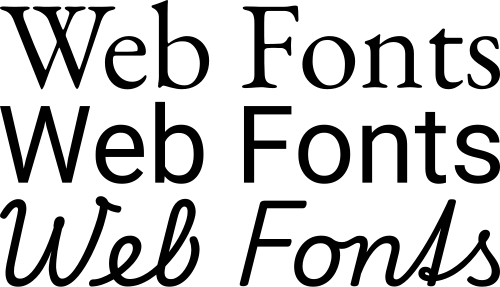
تُعنى الطباعة على الويب ، كغيرها من فنون الطباعة ، بتصميم الصفحات ، بما في ذلك تخطيطها واختيار أنواع الخطوط . وعلى عكس الطباعة التقليدية المعتمدة على الطباعة (حيث تكون الصفحة ثابتة بعد طباعتها )، فإن الصفحات المُخصصة للعرض على شبكة الإنترنت العالمية تواجه تحديات تقنية إضافية، وتتيح في الوقت نفسه فرصًا أوسع نظرًا لقدرتها على تغيير العرض ديناميكيًا . كانت تصاميم صفحات الويب الأولى بسيطة للغاية بسبب محدودية التكنولوجيا؛ أما التصاميم الحديثة فتستخدم أوراق الأنماط المتتالية (CSS) وجافا سكريبت وتقنيات أخرى لتحقيق رؤية مصمم الخطوط والعميل.
عند إنشاء لغة HTML لأول مرة، كانت أنواع الخطوط وأنماطها تُتحكم بها حصريًا إعدادات كل متصفح ويب . لم تكن هناك آلية تُمكّن صفحات الويب الفردية من التحكم في عرض الخط حتى قدمت نتسكيبfont عنصر <script> في عام 1995، والذي تم توحيده لاحقًا في مواصفات HTML 3.2. مع ذلك، كان يجب تثبيت خط الكمبيوتر المُحدد بواسطة عنصر <script> على جهاز المستخدم، أو استخدام خط احتياطي، مثل خط sans-serif أو monospacefont الافتراضي للمتصفح . نُشرت أول مواصفات CSS في عام 1996، ووفرت نفس الإمكانيات.
صدرت مواصفات CSS2 عام 1998، وسعت إلى تحسين عملية اختيار الخطوط بإضافة ميزات مطابقة الخطوط وتوليفها وتنزيلها. لم تلقَ هذه التقنيات رواجًا كبيرًا، وتم حذفها في مواصفات CSS2.1. مع ذلك، أضاف متصفح إنترنت إكسبلورر دعمًا لميزة تنزيل الخطوط في الإصدار 4.0 ، الذي صدر عام 1997. [ 1 ] أُدرجت ميزة تنزيل الخطوط لاحقًا في وحدة خطوط CSS3، ومنذ ذلك الحين تم تطبيقها في متصفحات سفاري 3.1 وأوبرا 10 وموزيلا فايرفوكس 3.5 . وقد أدى ذلك إلى زيادة الاهتمام بتصميم الخطوط على الويب، فضلًا عن زيادة استخدام ميزة تنزيل الخطوط.
CSS1
في أول مواصفات CSS، [ 2 ] حدد المؤلفون خصائص الخط من خلال سلسلة من الخصائص:
font-familyfont-stylefont-variantfont-weightfont-size
تم تحديد جميع الخطوط بالاسم فقط. وبخلاف الخصائص المذكورة أعلاه، لم يكن لدى المصممين أي وسيلة لتنسيق الخطوط، ولم تكن هناك آلية لاختيار الخطوط غير الموجودة على نظام العميل.
خطوط آمنة للاستخدام على الويب
الخطوط الآمنة للويب هي خطوط حاسوبية يُتوقع وجودها على نطاق واسع من أنظمة الحاسوب ، ويستخدمها مُنشئو محتوى الويب لزيادة احتمالية عرض المحتوى بالخط المُختار. إذا لم يكن لدى زائر موقع ويب الخط المُحدد، يحاول متصفحه اختيار بديل مشابه، بناءً على الخطوط الاحتياطية التي حددها المُنشئ والعائلات العامة ، أو يستخدم استبدال الخطوط المُعرّف في نظام تشغيل الزائر.
خطوط مايكروسوفت الأساسية للويب
لضمان حصول جميع مستخدمي الإنترنت على مجموعة أساسية من الخطوط، أطلقت مايكروسوفت مبادرة الخطوط الأساسية للويب عام ١٩٩٦ (والتي انتهت عام ٢٠٠٢). وتشمل الخطوط المتاحة Arial و Courier New و Times New Roman و Comic Sans و Impact و Georgia و Trebuchet و Webdings و Verdana ، وذلك بموجب اتفاقية ترخيص المستخدم النهائي التي سمحت بتوزيعها بحرية مع تقييد بعض حقوق استخدامها. وقد جعلها انتشارها الواسع عنصرًا أساسيًا لمصممي مواقع الويب. ومع ذلك، لا تتضمن معظم توزيعات لينكس هذه الخطوط افتراضيًا.
سعت CSS2 إلى زيادة الأدوات المتاحة لمطوري الويب من خلال إضافة توليف الخطوط، وتحسين مطابقة الخطوط، وإمكانية تنزيل الخطوط عن بُعد. [ 3 ]
تمت إزالة بعض خصائص الخطوط في CSS2 من CSS2.1 ثم أُضيفت لاحقًا إلى CSS3. [ 4 ] [ 5 ]
الخطوط الاحتياطية
تسمح مواصفات CSS بإدراج عدة خطوط كخطوط احتياطية. [ 6 ] في CSS، font-familyتقبل الخاصية قائمة بأنواع الخطوط مفصولة بفواصل، كما يلي:
font-family : "Nimbus Sans L" , Helvetica , Arial , sans-serif ;الخط الأول المحدد هو الخط المفضل. إذا لم يكن هذا الخط متوفرًا، يحاول متصفح الويب استخدام الخط التالي في القائمة. إذا لم يتم العثور على أي من الخطوط المحددة، يعرض المتصفح خطه الافتراضي. وتتكرر هذه العملية نفسها لكل حرف على حدة إذا حاول المتصفح عرض حرف غير موجود في الخط المحدد.
عائلات الخطوط العامة
لمنح مصممي المواقع الإلكترونية بعض التحكم في مظهر الخطوط على صفحاتهم، حتى في حال عدم توفر الخطوط المحددة، تسمح مواصفات CSS باستخدام عدة عائلات خطوط عامة. صُممت هذه العائلات لتقسيم الخطوط إلى فئات متعددة بناءً على مظهرها العام. وعادةً ما تُحدد كخيار أخير ضمن سلسلة من الخطوط البديلة، في حال عدم توفر أي من الخطوط التي حددها المصمم. ولعدة سنوات، كانت هناك خمس عائلات خطوط عامة: [ 6 ]
- الخطوط التي لا تحتوي على علامات زخرفية، أو زوائد، على حروفها. غالباً ما تعتبر هذه الخطوط أسهل في القراءة على الشاشات. [ 7 ]
- الخطوط التي تحتوي على علامات زخرفية، أو حروف ذات زوائد، على حروفها. تُستخدم هذه الخطوط تقليديًا في الكتب المطبوعة.
- الخطوط التي تكون فيها جميع الأحرف متساوية العرض.
- الخطوط التي تشبه الكتابة اليدوية. قد تتميز هذه الخطوط بمظهرها الزخرفي، ولكن يصعب قراءتها بأحجام صغيرة، لذا فهي تُستخدم عادةً باعتدال.
- الخطوط التي قد تحتوي على رموز أو خصائص زخرفية أخرى، ولكنها لا تزال تمثل الحرف المحدد.
خطوط CSS تعمل في الإصدار الرابع مع دعم محدود من المتصفحات
اعتبارًا من فبراير 2024تقترح مجموعة عمل CSS التابعة لـ W3C أن تحدد الأنظمة خطًا افتراضيًا باستخدام uiالوسوم؛ [ 8 ] وحتى التاريخ نفسه، لم يتم دعم هذه الوسوم على نطاق واسع بعد. [ 9 ]
- واجهة المستخدم النظامية
- الخطوط الافتراضية على نظام معين: الغرض من هذا الخيار هو السماح لمحتوى الويب بالتكامل مع مظهر وشكل نظام التشغيل الأصلي.
- ui-serif
- الخطوط الافتراضية على نظام معين بنمط serif
- واجهة المستخدم بدون سيريف
- الخطوط الافتراضية على نظام معين بنمط sans-serif
- واجهة المستخدم أحادية المسافة